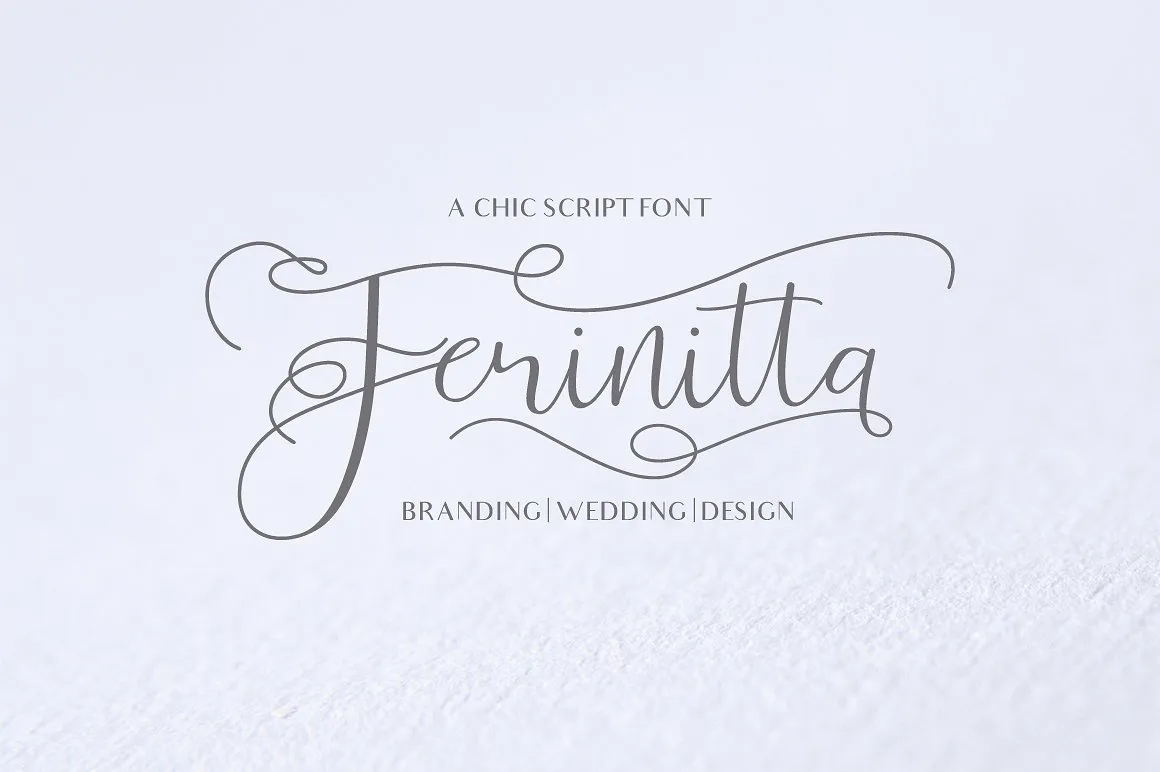
A fonte Ferinitta Calligraphy oferece uma experiência visual envolvente para quem busca adicionar um toque diferenciado a seus projetos digitais ou impressos. Esta chic script é ideal para aqueles que desejam dar vida aos textos com um estilo elegante e de autêntica mão de escrever. Com um fluxo fluido, essa fonte moderna é perfeita para incorporar em grandes volumes de texto, seja em uma identidade visual, um logotipo, convites ou até mesmo em elementos de design de produto e fotografia. Ef_Studio criou Ferinitta Calligraphy Font com amor, pensando nas necessidades dos designers que desejam dar um toque pessoal aos seus trabalhos. É uma opção perfeita para aqueles que buscam personalizar seu layout ou projeto sem sacrificar a elegância e sofisticação que o design de fontes pode oferecer.